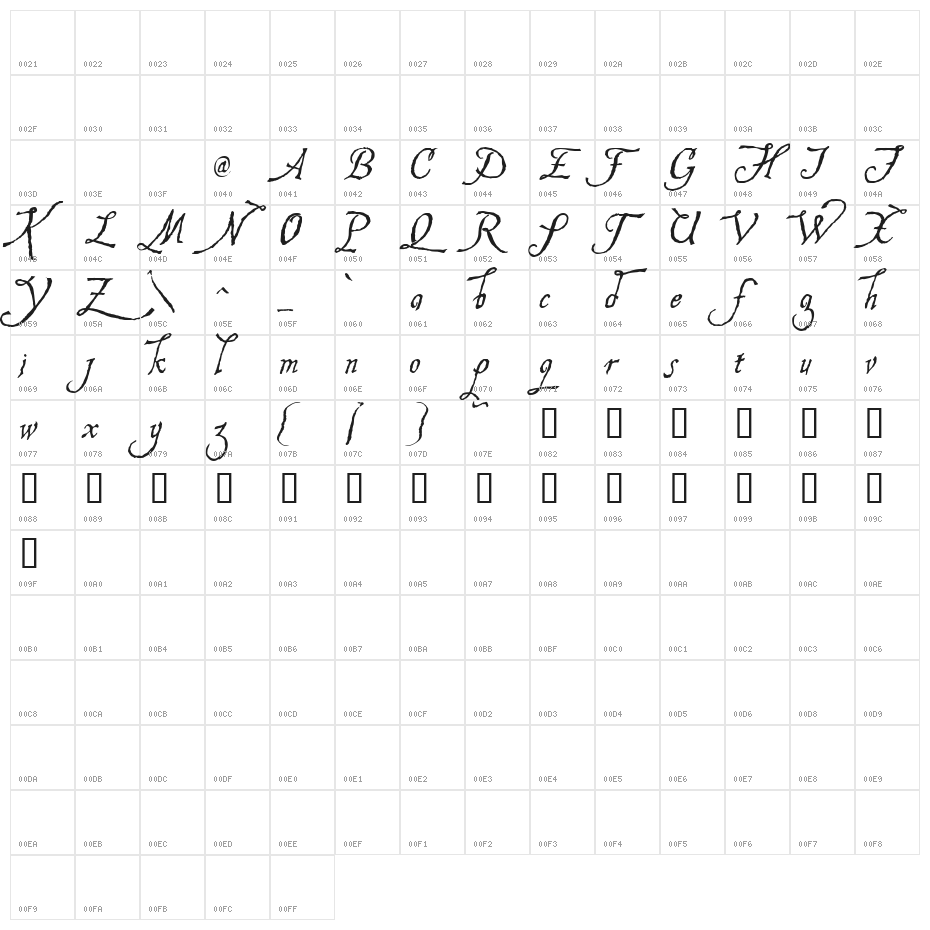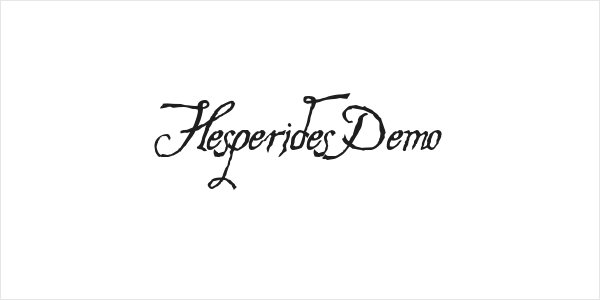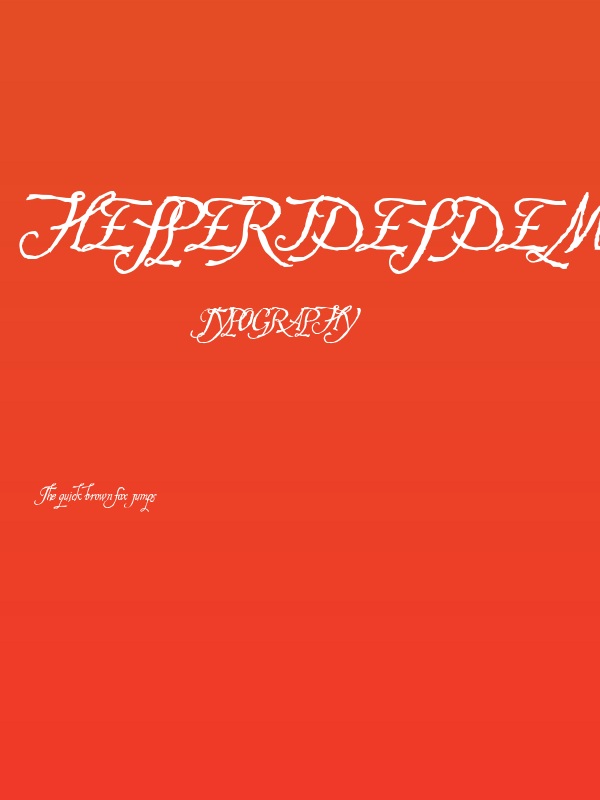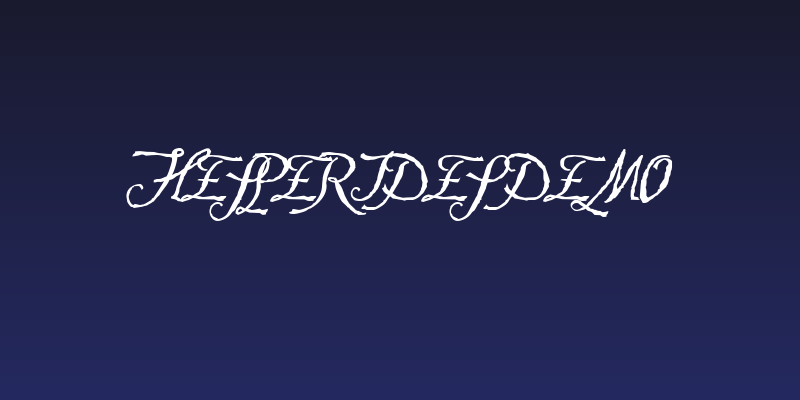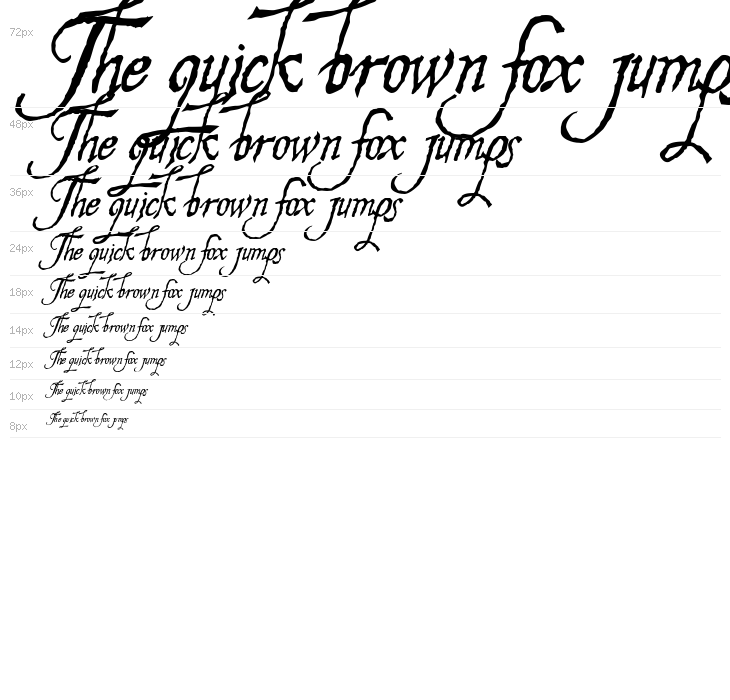
Hesperides Demo Font
| 分类 | Script |
| 斜体 | Yes |
| 宽度 | Condensed |
| 整体风格 | Vintage |
| 使用场景 | Headlines, Logos, Invitations |
| 推荐项目 | Ideal for wedding invitations, historical documents, branding for luxury products, and decorative headlines. |